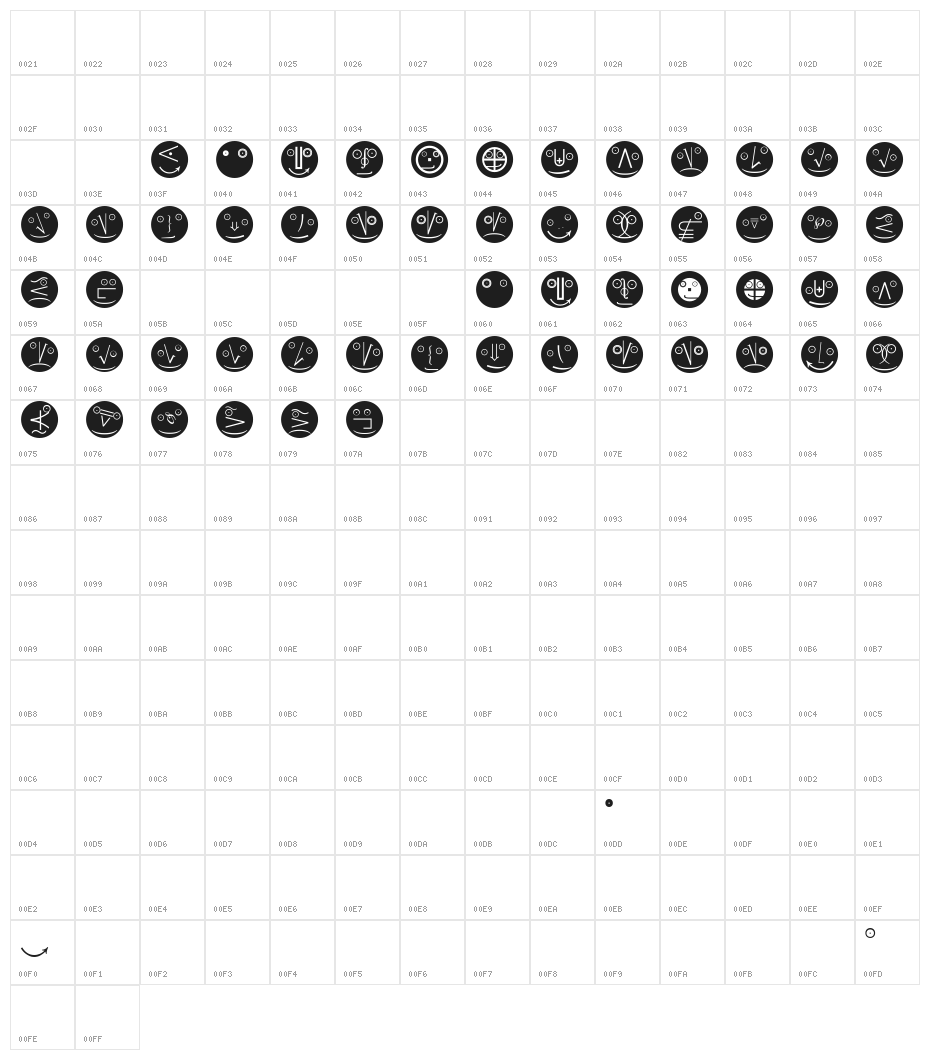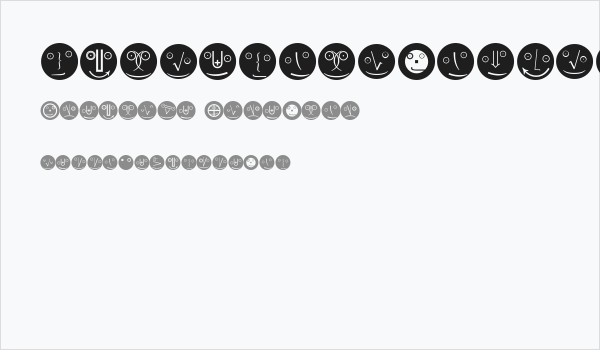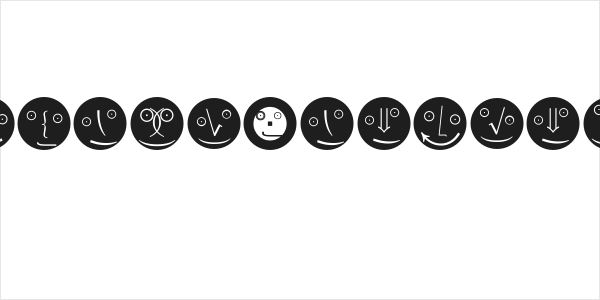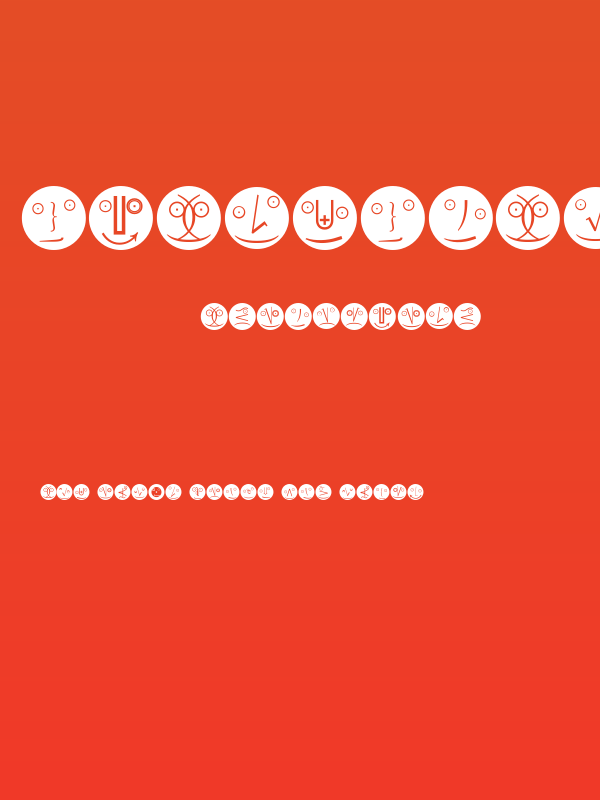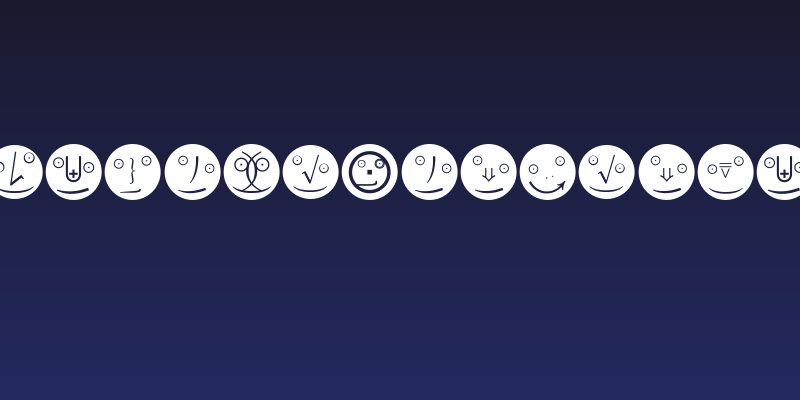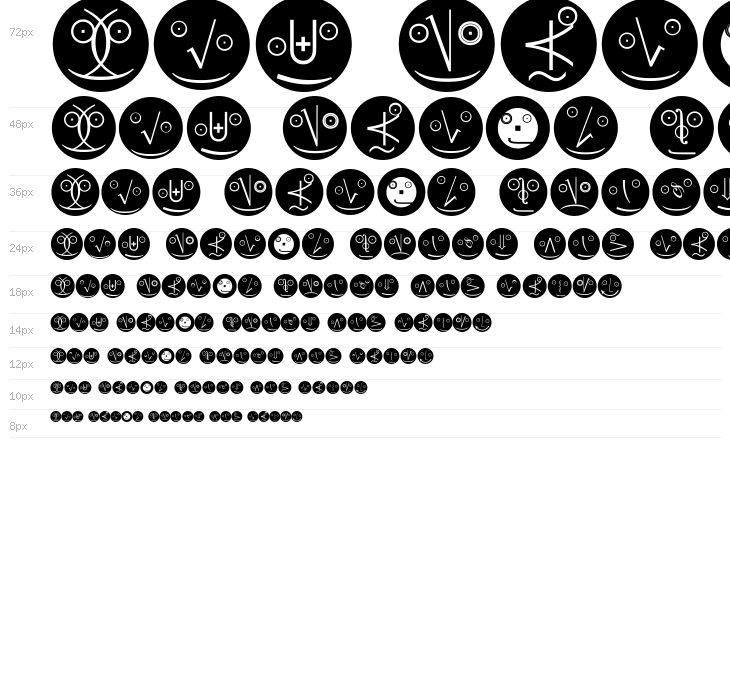
MathEmoticonsInverse Font
| Caz de utilizare | Digital communication, Educational tools |
| Proiecte propuse | Ideal for digital communication platforms, educational tools, or any project requiring a playful and abstract representation of emotions. |